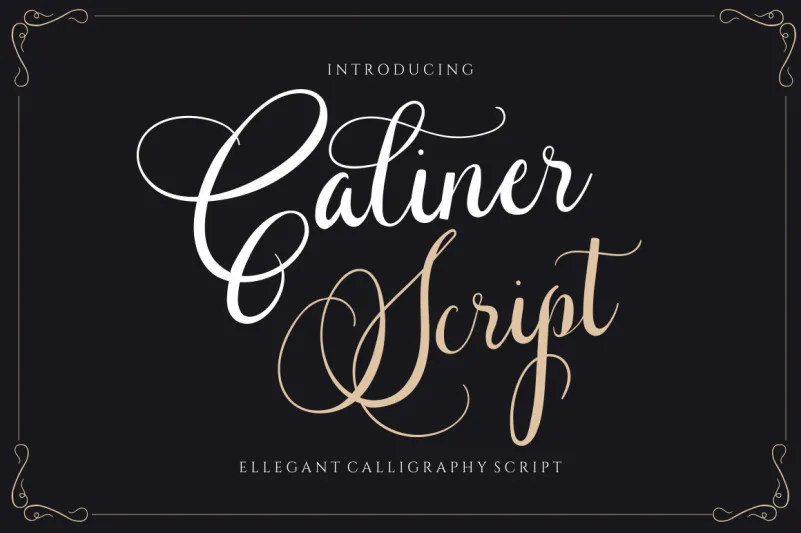
Esta é uma linda e delicada fonte script que exala elegância e classe. Este tipo foi criado meticulosamente para aqueles que buscam um visual agradável e rejuvenescedor em seus projetos. Caliner Font não apenas adiciona um toque sofisticado aos textos, mas também oferece uma maneira única de personalizar qualquer design. Seja você um designer profissional ou iniciante, este tipo traz beleza e modernidade para seus trabalhos. Reconhecida pelo seu designer ReyreyBlue, Caliner Font é perfeita para aqueles que desejam dar um novo impulso a suas criações.